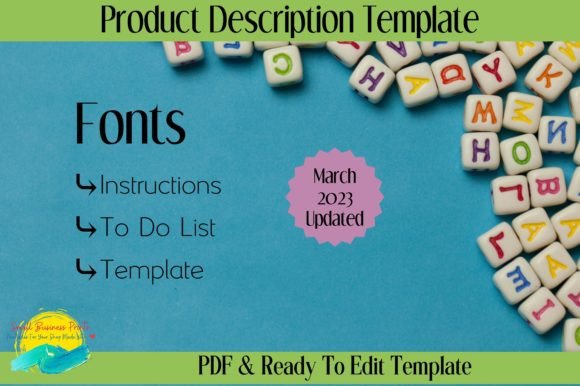
Product Description Template - Fonts
Việc tìm kiếm các thành phần thiết kế phù hợp có thể là một thách thức, nhưng Product Description Template - Fonts cung cấp một bộ sưu tập đặc biệt giúp nâng tầm công việc của bạn ngay lập tức.
Được chế tác với độ chính xác cao, Product Description Template - Fonts cung cấp các vector sạch, kiểu chữ mượt mà và giấy phép thương mại để bạn yên tâm.